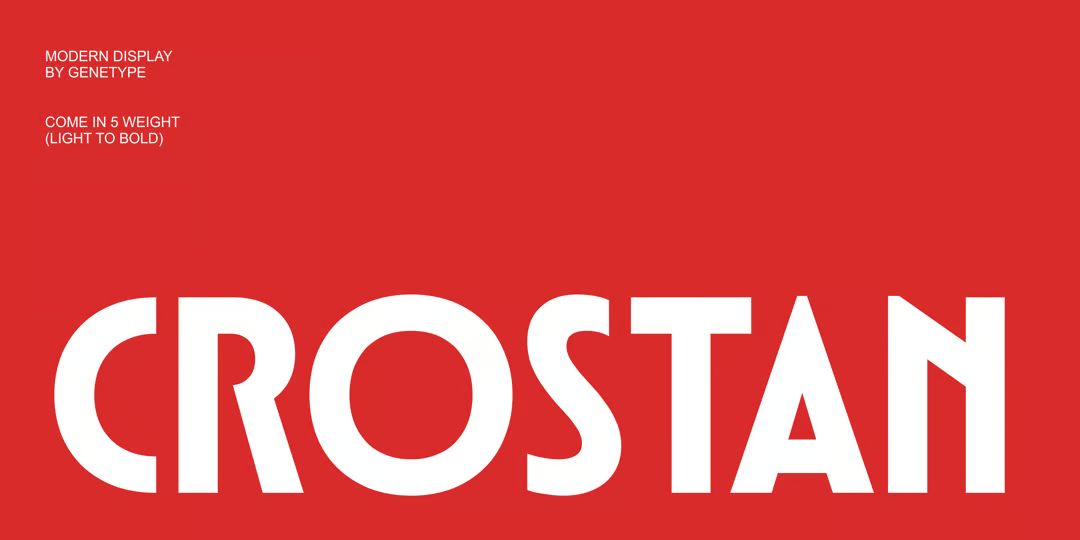
Crostan
アール・デコ風味があるモダンなサンセリフディスプレイ。バウハウススタイルを取り入れてると説明にあり、確かにアール・デコの要素はありつつ、レトロになりすぎず割とスタイリッシュな書体に仕上がっている。大文字のみだが小文字には一部グリフ違いの字が入っており、デフォルトの C は見ての通りの半円状、小文字の方にはほぼ円に近い C が入っていたりと他にも変化が楽しめるようになっている。5ウェイト。